כשמדברים על בניית מותג, רובנו בדרך כלל חושבים על צבעים, לוגו, אולי על סלוגן. אבל יש מרכיב עיצובי אחד שבשקט בשקט קובע את התחושה שאנחנו מקבלים ממותג: הטיפוגרפיה.
בחירה יצירתית של פונטים לא רק משפיעה על המראה, אלא מעצבת את האישיות של המותג ומגדירה את הקול שבו הוא מדבר אל הקהל שלו.
במאמר הזה נעמיק את ההבנה בנוגע לקשר בין העיצוב של האותיות לבין יצירת מותג בלתי נשכח.
טיפוגרפיה כבסיס לעיצוב מותג
הטיפוגרפיה היא השגרירה השקטה אך העוצמתית של המותג. המים השקטים שחודרים עמוק. היא יכולה לשדר רצינות, שובבות, יוקרה או נגישות – כול זה רק דרך בחירת הפונט.
כאשר משתמשים בפונט ייחודי שנבחר בקפידה, המותג מקבל זהות ויזואלית ברורה שאפשר לזהות בקלות גם ללא לוגו. מותגים שמשכילים להבין את זה מקפידים לבחור פונטים שתואמים את הערכים שלהם – ולא נופלים על ברירת המחדל הכמעט מתבקשת.
איך טיפוגרפיה יצירתית יוצרת זכירות
המוח האנושי נוטה לזהות דפוסים במהירות רבה. כאשר פונט מעוצב בקפידה ומשקף את האופי של המותג – הוא נחקק עמוק והיטב בזיכרון של כל רואיו.
זו הסיבה המרכזית לכך שמותגים חזקים יוצרים לעצמם טיפוגרפיה מותאמת או בוחרים בפונטים ייחודיים שמובילים את השפה החזותית שלהם לאורך זמן.
טיפוגרפיה יצירתית יכולה להיות מהות ההבדל בין מותג שנבלע ברעש ולא תופס מקום, לבין כזה שתופס גם את העין וגם את הלב.
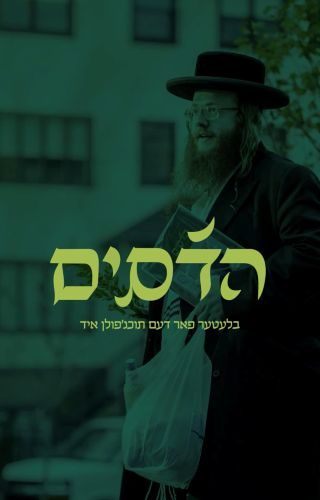
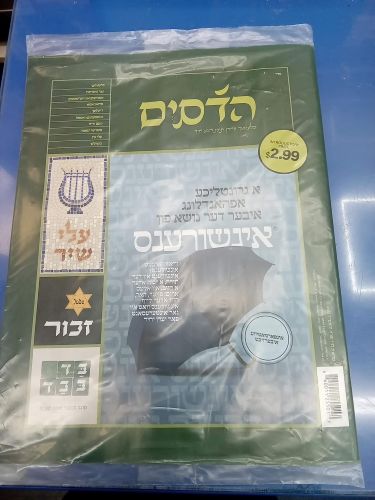
הקשר בין פונטים לקול המותג
לפונט יש קול. הוא יכול להיות קול רך או חד, קליל או כבד, צעיר או בוגר. ברגע שמבינים ומצליחים לשמוע את הקול של המותג – קל יותר לבחור את הפונט שידבר אותו החוצה בשפה הנכונה, כזה שמי שיקרא אותו יעשה זאת בטון ובקול של המותג.
כך, למשל, פונט סריפי אלגנטי יתאים לעסק שרוצה לשדר יוקרה ומסורת, לעומת פונט גיאומטרי שיקלע בול לעסק טכנולוגי.
פונטים כתב יד בעברית, לדוגמה, הם דרך מצוינת לשדר אנושיות וקרבה: כאשר משתמשים בהם נכון, הם מעניקים למותג תחושה של נגיעה אישית וייחודית, וקוראים ללקוחות בקול עדין להצטרף.
דגשים לבחירת פונטים בעברית למותגים:
- בחרו פונט שמתאים לשפה העיצובית הכללית של המותג, כזה שישתלב בה בטבעיות
- ודאו שהפונט קריא – גם בגודל קטן. הטכנולוגיה המתפתחת מצמצת את המסכים עוד ועוד
- התאימו את הפונט לפלטפורמה: פונט אחד לדיגיטל, פונט אחד לדפוס, פונט נוסף לשלטי חוצות ועוד
- בדקו שהפונט תומך בעברית מלאה, כולל ניקוד אם יש צורך. אל תתנו לו ליפול על שפה
- חפשו פונטים עם אופי – לא משהו שנראה כמו כולם ונראה אצל כולם. אחרת מה עשינו פה?!
זכרו: טיפוגרפיה אומנותית יכולה להכניס נגיעה מפתיעה ומרעננת למותג – במיוחד כשמדובר בעסקים יצירתיים או מתחומי האומנות, האופנה והעיצוב, אבל בהחלט לא רק לכאלה.
סיכום
לסיכום, בעולם שבו התקשורת מתבצעת יותר ויותר דרך מסכים, חשוב לבחור פונטים מושלמים לרשתות חברתיות – כאלה שמיועדים מראש ועוצבו לשימוש במסכים ומבטיחים קריאות מרבית דרך כל מכשיר.
זכרו שמותג חזק לא נבנה רק על סלוגן חד, לוגו יפה או מערכת שיווק משומנת. הוא נבנה מהפרטים הקטנים – כולל צורת האותיות או כמה נוח לקרוא אותו ולצפות בו. טיפוגרפיה יצירתית יכולה להפוך את הקול של המותג לברור, חכם ובלתי נשכח.
מה ההבדל בין פונטים לדפוס לפונטים לדיגיטל?
פונטים לדיגיטל מותאמים במיוחד למסכים – הם חדים, קריאים גם בגדלים קטנים, ונראים טוב בכל רזולוציה. פונטים לדפוס יכולים להיות עשירים בפרטים אבל פחות מתאימים למסך.
איך אדע איזה פונט מתאים לעסק שלי?